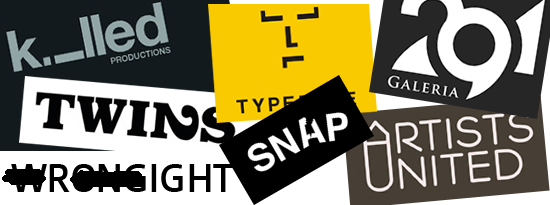
72 logos creativos con tipografía para inspiración
Los logotipos son imágenes visuales que representan a una marcas, por lo que transmiten un mensaje que la gente fácilmente reconoce.
En algunas ocasiones he comentado sobre tipos de letras llamativas para logotipos, que se pueden emplear perfectamente, también tenemos otros tipos de letras para el diseño de logotipos. Una tipografía acertada se puede emplear perfectamente en un texto para un logotipos. La tipografía tiene una gran importancia en el diseño de un logo, pues la mayoría de de ellos se componen de una “marca” y una “tipografía”.
La “marca“, siempre es visual, y puede ser sobria, moderna, lúdica, que apenas se vea o que resalte. La “tipografía”, establece el estado de ánimo para el tono de la empresa (informal, lúdica, etc.), de ese modo realza a la “marca” por lo que combinando los dos conceptos, conseguimos logotipos creativos y brillantes.
Pero también podemos crear logos con solo la tipografía, como puedes ver en el artículo 72 Creative And Smart Typographic Logo Inspiration, de 1stwebdesigner. Una colección de 72 logotipos realizados por diferentes diseñadores con gran talento en donde sólo han empleado la tipografía de una manera muy acertada. Emplean Solo una o dos palabras en negativo, positivo, o en colores, donde nos permiten la creación de asociaciones muy interesantes.